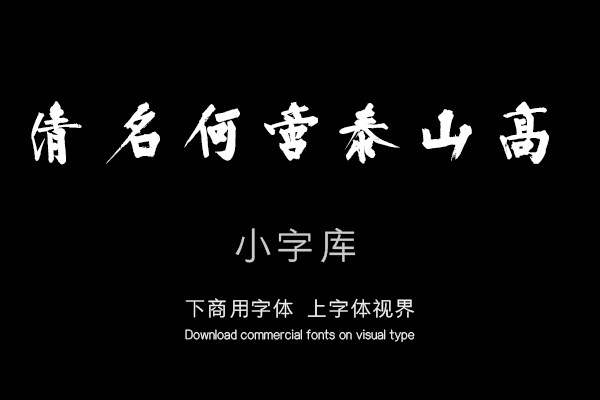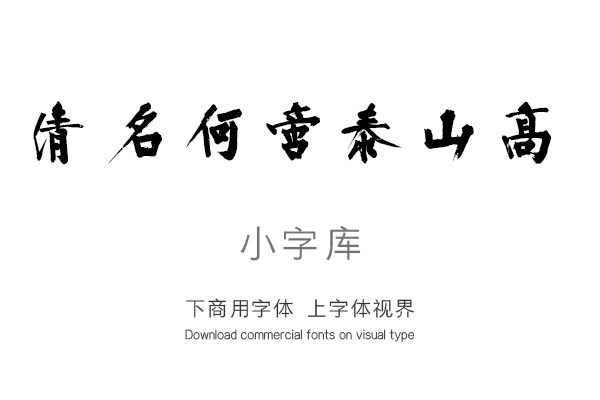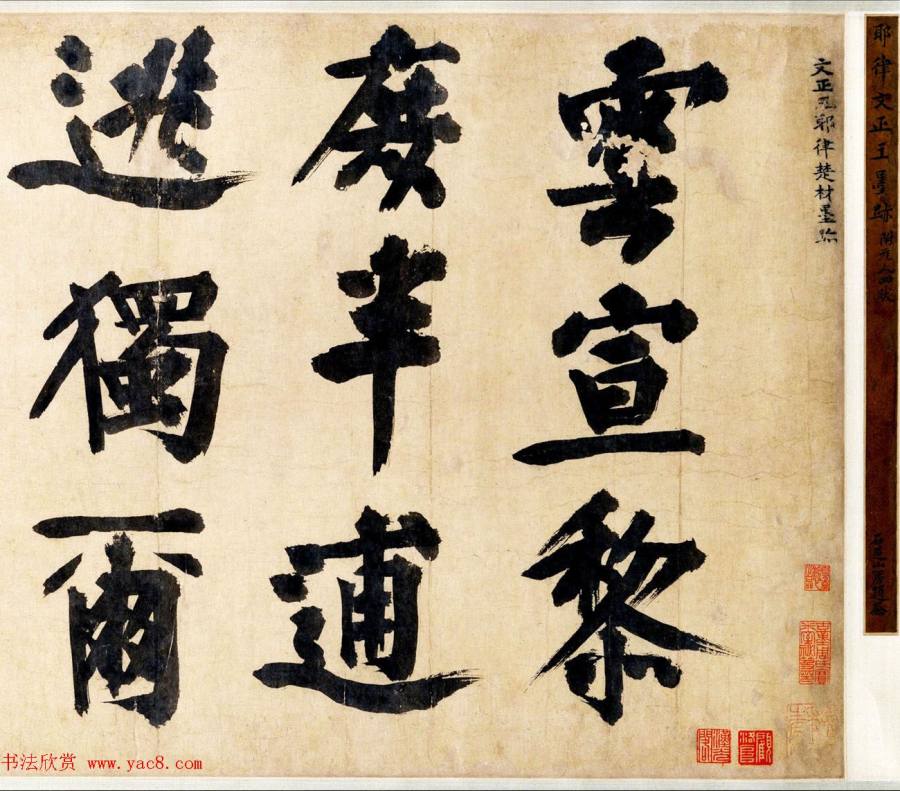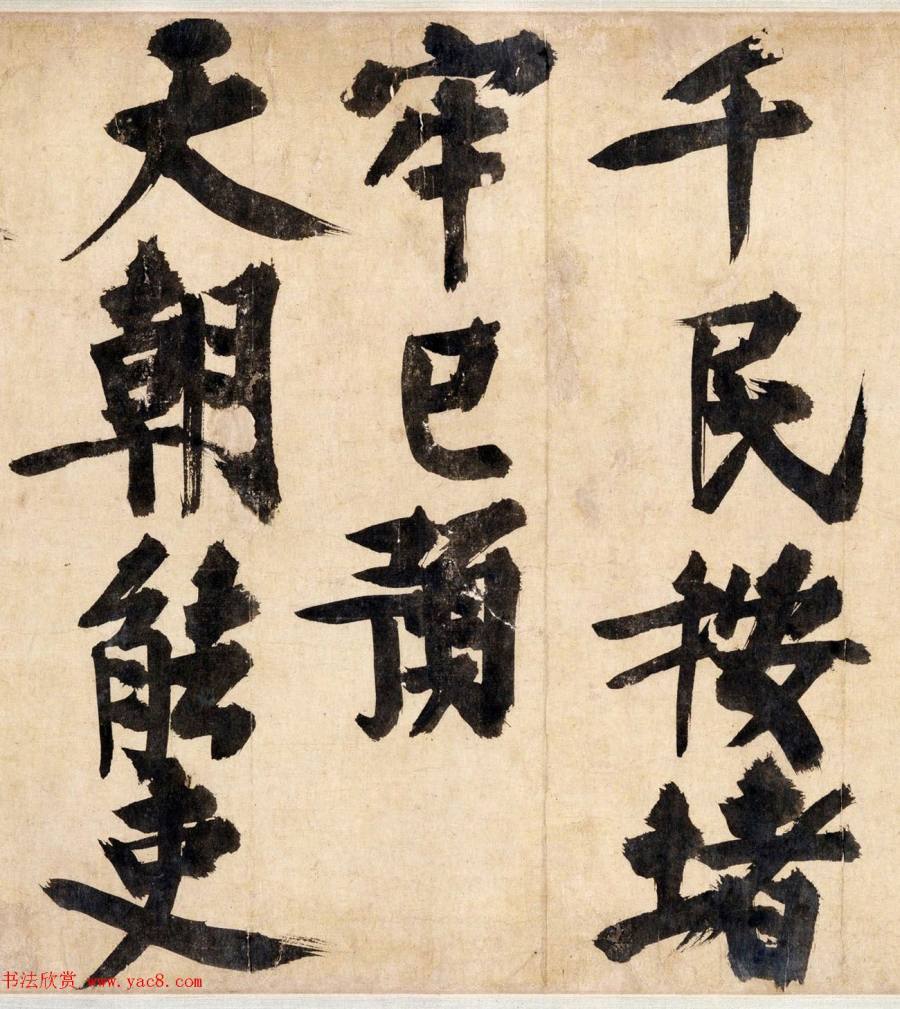
《汉标文正王耶律楚材送刘满诗卷》是一款根据元代耶律楚材经典书法作品《送刘满诗卷》经过再次调整制作的小字库,该小字库共收录了该真迹作品中约71个字体。单字授权
雲宣黎庶半逋逃,獨爾千民按堵牢。已預天朝能吏數,清名何啻泰山高。庚子之冬十月既望陽門劉满將行索詩,以此贈之,賞其能治也。暴官猾吏豈不媿哉。玉泉